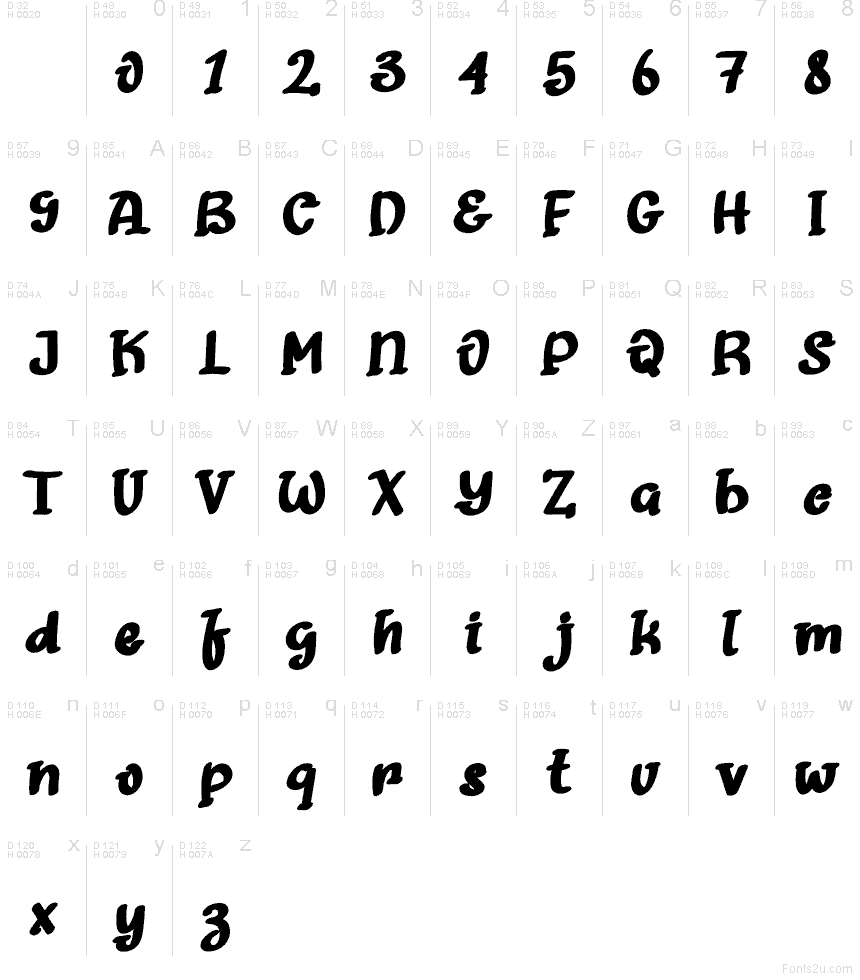
Snowhite Grace Demo
Snowhite Grace è un font brush gratuito con forme fluide, dipinte a mano e linee morbide e arrotondate. I tratti collegati regalano un ritmo di scrittura armonioso, mentre gli ampi svolazzi aggiungono un tocco casual ed elegante senza risultare confusi.
Snowhite Grace è perfetto per biglietti d'invito, loghi, packaging, citazioni per i social media e titoli brevi, poiché lo stile a pennello conferisce un carattere naturale e artigianale al testo. Si adatta magnificamente ad accenti editoriali o loghi autografati, quando vuoi un tocco personale che mantenga un aspetto professionale e curato.